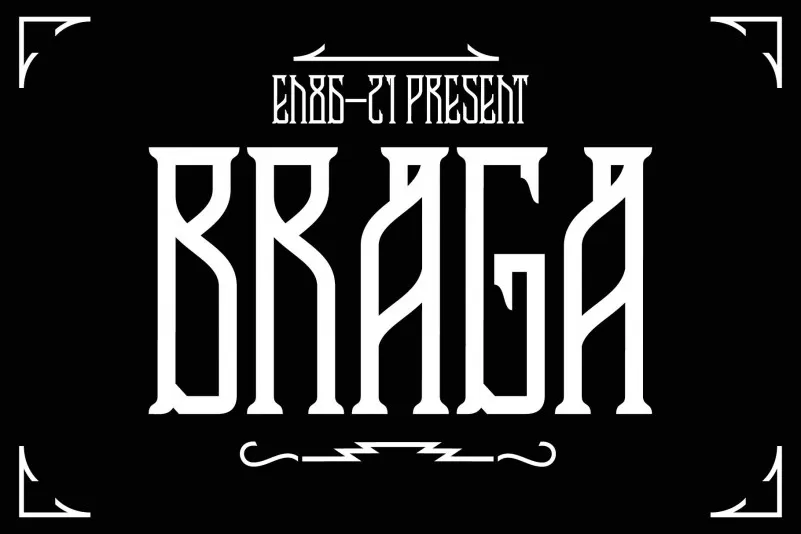
Braga Display Font – Download Grátis
A Braga Display Font é inspirada nos moldes clássicos das letras, uma escolha perfeita para quem busca um gótico moderno que pode se adequar tanto como texto principal quanto para criações visuais como logotipos ou pacotes de produtos. Esta fonte está disponível em formato OTF, incluindo letras maiúsculas e minúsculas, números e marcadores de pontuação básicos. Além disso, a família de recursos também oferece extras no formato EPS, proporcionando maior flexibilidade para o designer que busca incorporar essa fonte em seu trabalho. Inspirada nos estilos góticos clássicos da arte tipográfica, Braga é uma escolha conveniente para criar designs visuais modernos e elegantes.
Designer: EN86-21